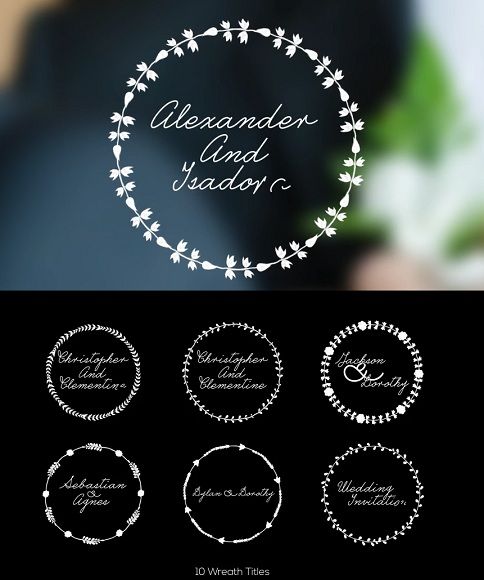
دانلود پروژه افتر افکت عروسی Wedding Animated Typeface
دانلود پروژه آماده افتر افکت عروسی متن
دانلود پروژه آماده افتر افکت عروسی با نام Wedding Animated Typeface از شرکت معروف ویدیو هایو.اگر می خواهید برای شروع فیلم های عروسی خود یا معرفی عروس و داماد و ....از متن ها و انیمیشن های زیبایی استفاده کنید این پروژه افتر افکت فیلم عروسی مناسب شماست.در این پروژه افتر افکت می توانید متن ها و انیمیش های زیبایی را ایجاد کنید و در ادیت فیلم عروسی خود از آن ها استفاده نمایید.کیفیت این پروژه 1920x1080 می باشد و شما برای اجرا کردن آن به هیچ پلاگین خاصی نیاز ندارید.توجه داشته باشید این پروژه آماده افتر افکت بر روی ورژن cs5.5 با بالا قابل اجرا می باشد.
ویژگی های پروژه افتر افکت عروسی Wedding Animated Typeface :
» 25 انیمیشن آماده تاج گل
» 10 عنوان متنی پیش ساخته شده آماده